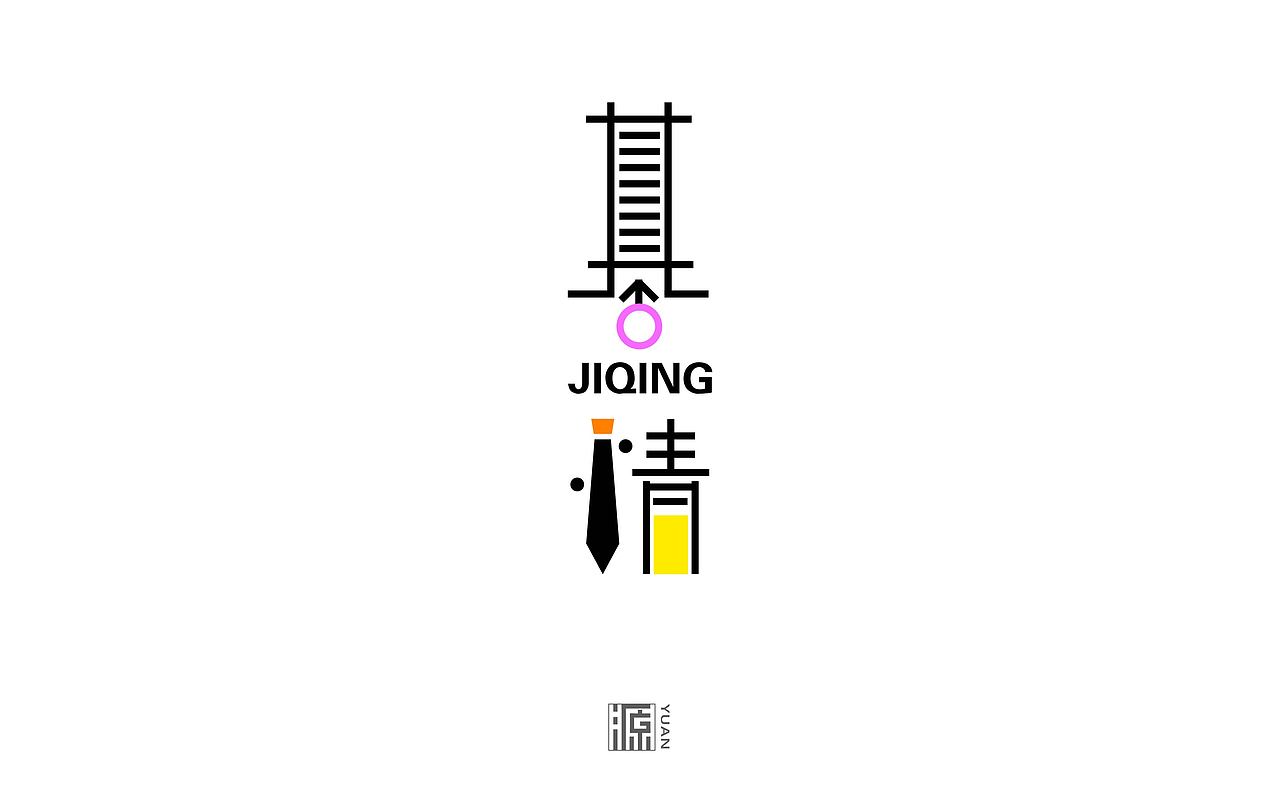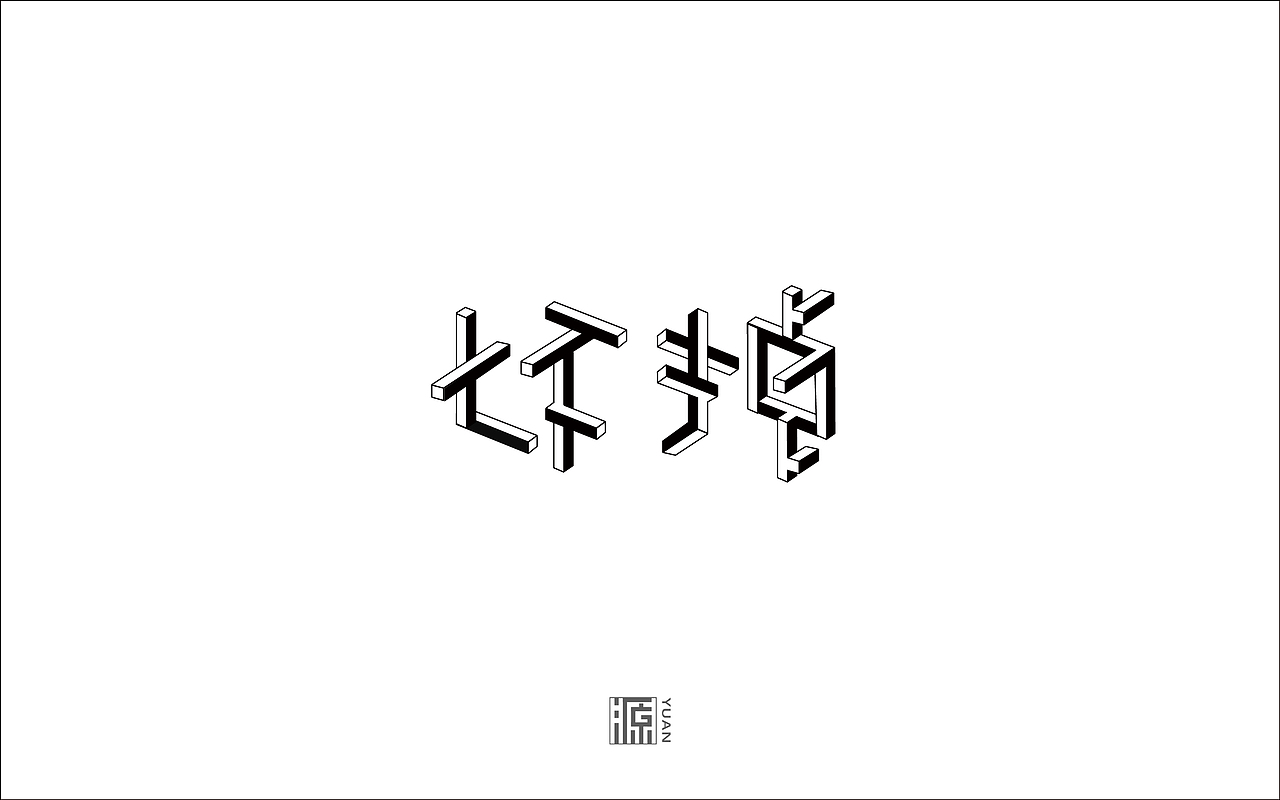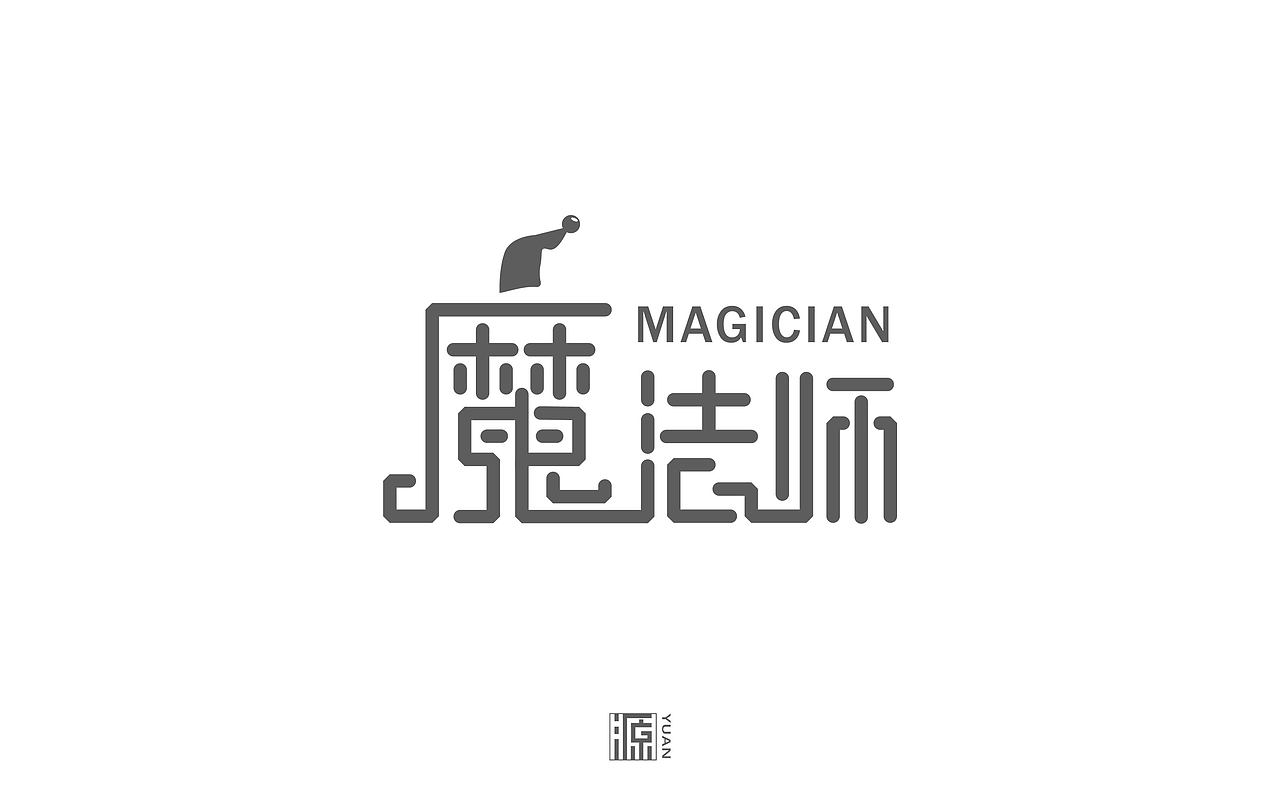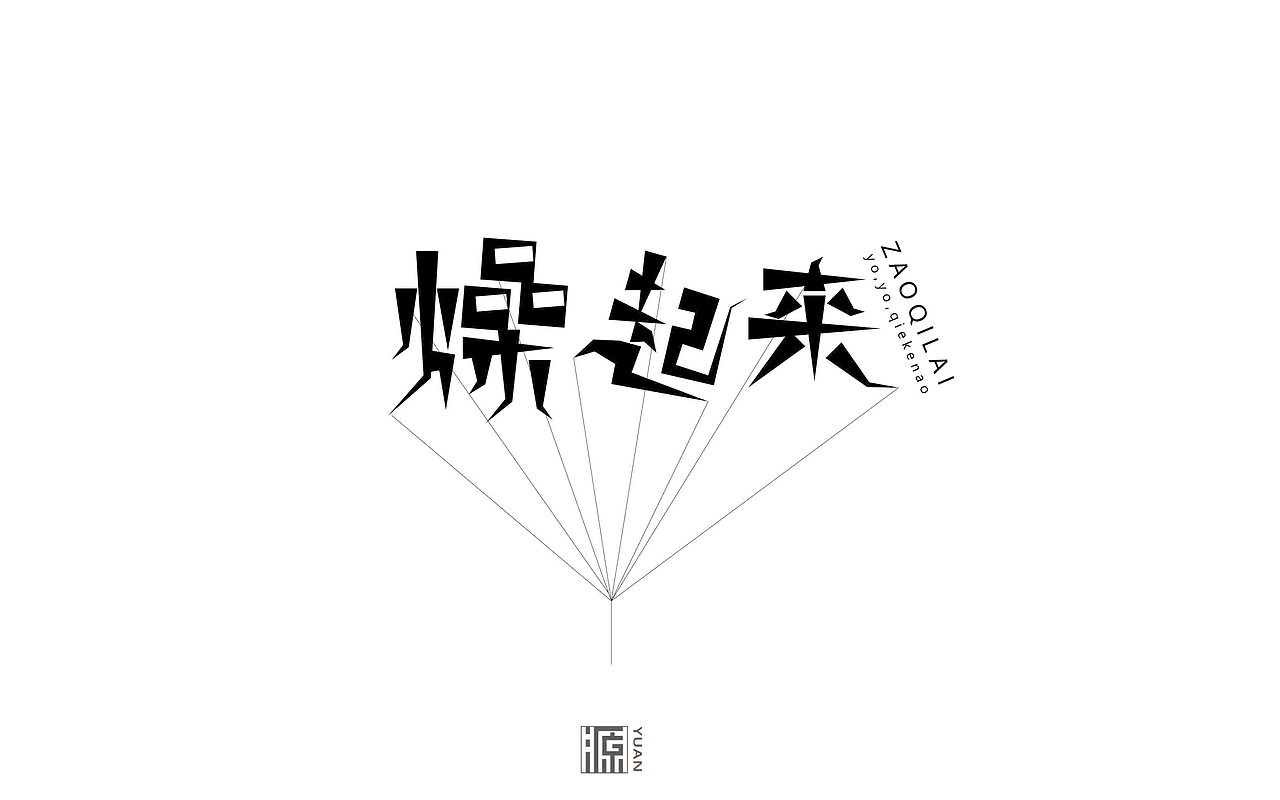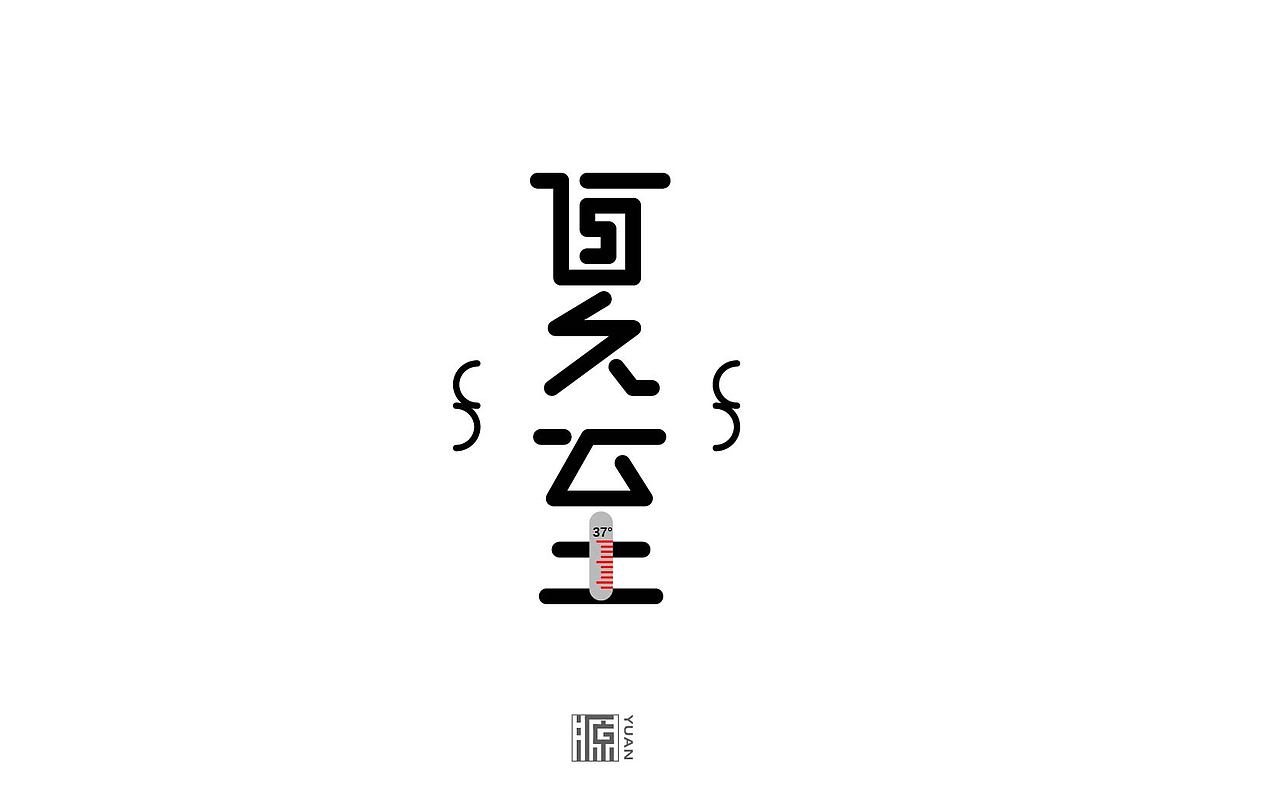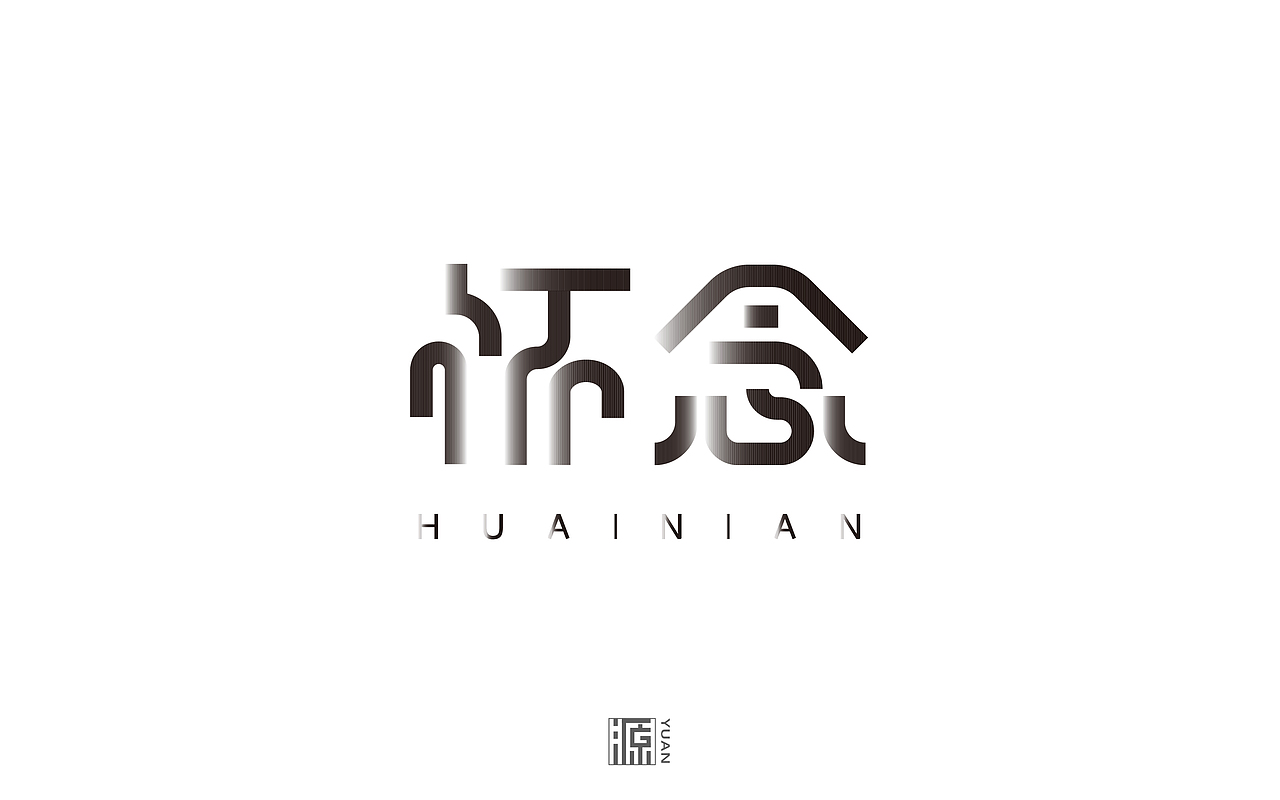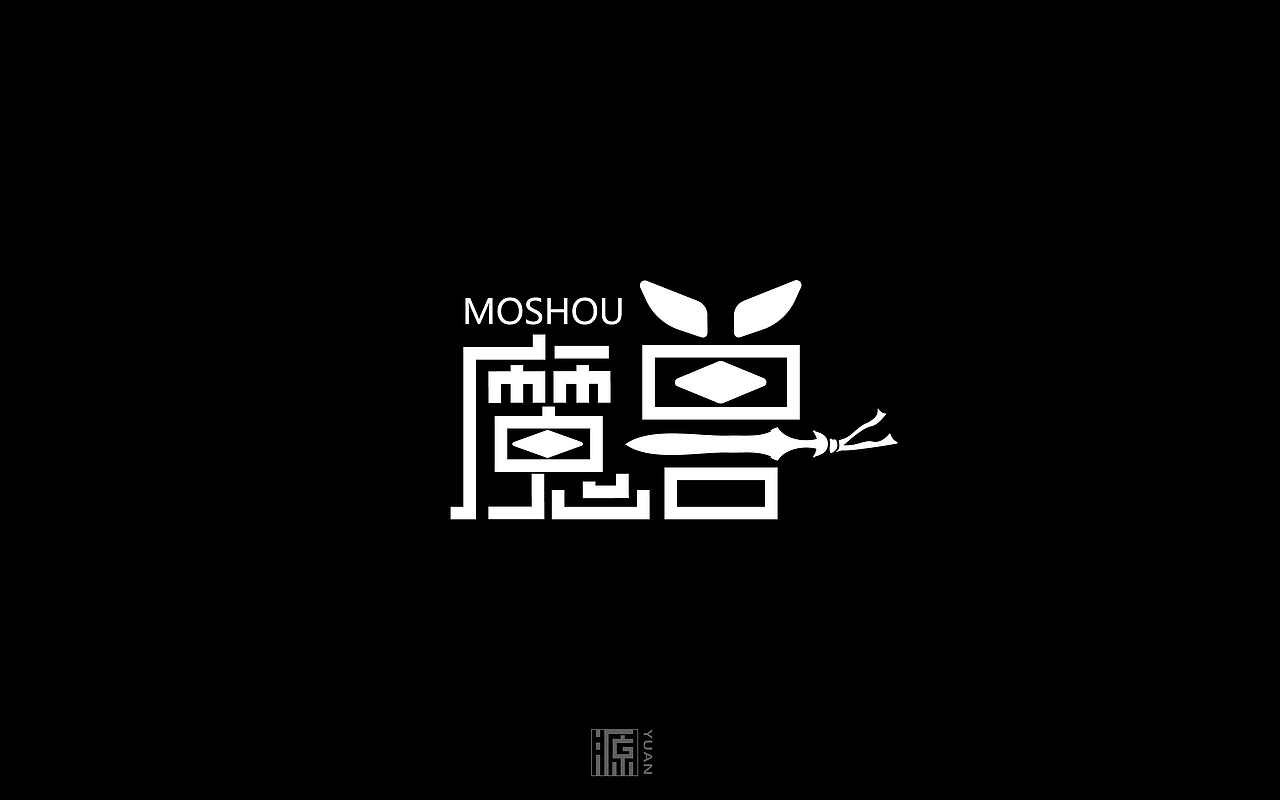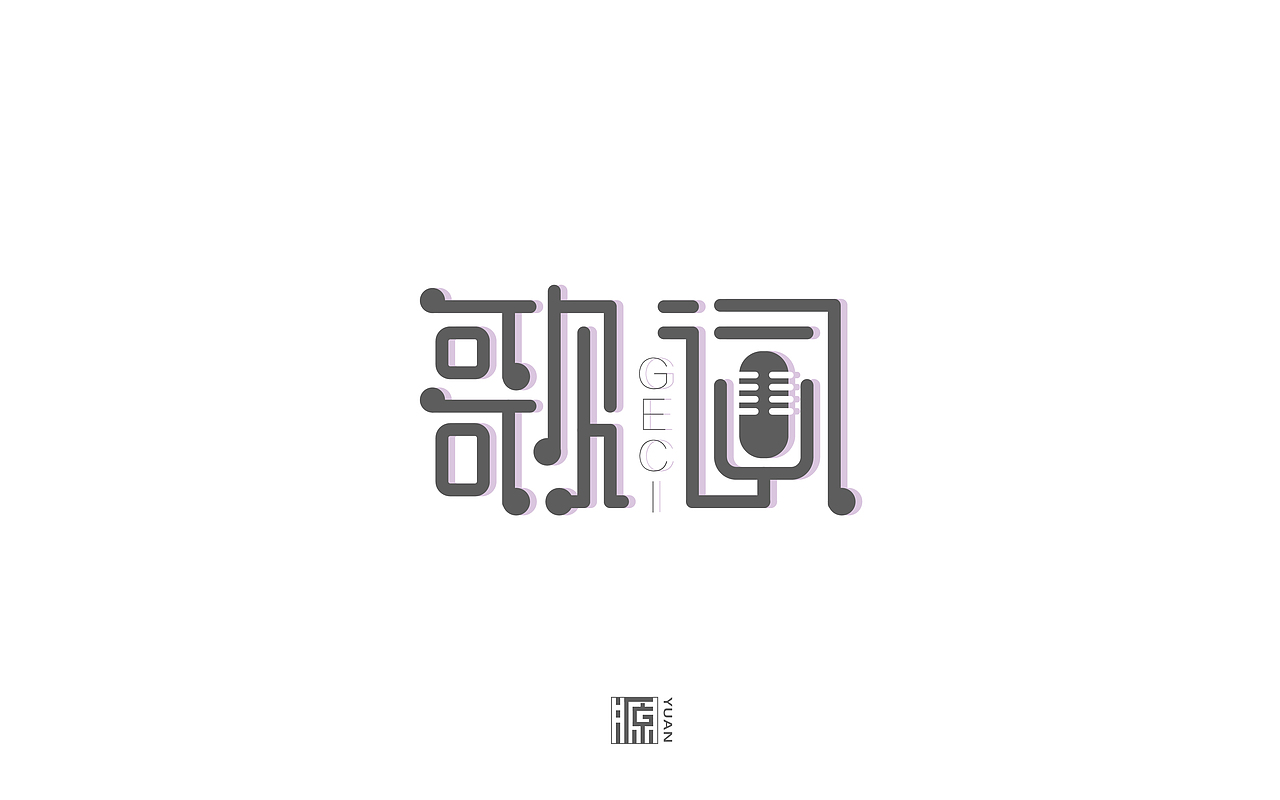
六月份字体合集
源仔仔
第一百天。
做字一件很乐趣的事,每个字体都是自己对字的感受和理解,就像每个人对生活的感悟和理解不同
学习做字像佳哥说的是一个没有邪恶,没有坏人,没有骗子,只有学习的爱的世界
以后可能不会天天去做字,但是我对待字会越来越严谨
字的好不好,我觉得是跟着自己感觉对的方向去,没有绝对的正确和完美,只有不断去减少错误,就是正确的。
《哈尔的移动城堡》 重温了这部动漫电影(挺好的电影)
老友
萤火虫 想到小时候抓萤火虫装在透明的瓶子里 是第一个有动效的文字(感谢阿凯的技术教学)
醉意
糊涂 这是手涂的字,拍照放到软件扩展调整。
过瘾
安砂鱼场 广告设计课上,老师布置的商业案例的一个商家的名称
欢喜
城 城门
激情 男性的符号,还有领带
坏掉 福州画室一个很有艺术气息老师的书
魔法师
平凡而伟大 父亲节那天做的 还发给我老爸,他只回了一个字“哦”
燥起来
夏至 天气越来越热
高温 那天真的温度很高 可以煎蛋
怀念
魔兽 有童心的感觉
往事
歌词
白熊 字是酒瓶的形状) 南门喝喝小酒吧的酒 淡淡的水果香
吸血鬼日记 看的速度慢,已经到第七季我才看到第三季